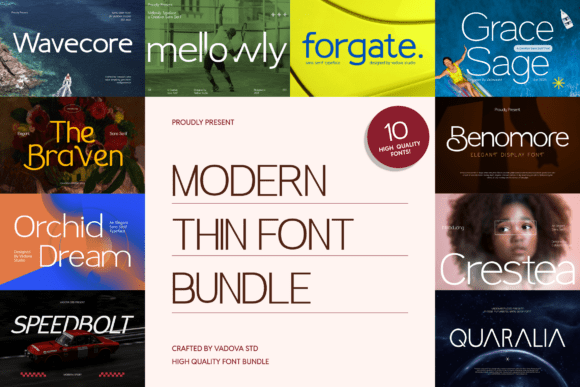
Modern Thin Bundle
Modern Thin Font Bundle – Revue détaillée
Le Modern Thin Font Bundle s’impose comme la référence incontournable pour tous les créatifs recherchant une typographie à la fois légère, élégante et ultra‑moderne. Cette collection regroupe des polices ultra‑minces qui allient clarité et raffinement, idéales pour les projets où la sobriété et le style sont primordiaux.
Points forts du bundle
- Design épuré : des proportions parfaitement équilibrées qui donnent une impression d’espace et de légèreté.
- Excellent rendu à l’écran : chaque fonte a été optimisée pour les interfaces digitales (sites web, applications mobiles, UI/UX).
- Lisibilité assurée : même en très petite taille, les caractères restent nets grâce à un tracé précis.
- Versatilité : convient aux identités de marque, aux mises en page éditoriales, aux packagings haut de gamme, à la mode et aux projets de branding.
Pourquoi choisir Modern Thin Font Bundle pour vos projets?
Que vous créiez une identité visuelle minimaliste, un magazine de mode ou un site e‑commerce premium, ce bundle offre une base typographique solide qui rehausse immédiatement le caractère professionnel de votre travail. Les traits fins apportent une touche de luxe sans sacrifier la lisibilité, ce qui est essentiel pour les titres, les sous‑titres et les citations accrocheuses.
Utilisations idéales
- Branding et logotypes modernes
- Mises en page éditoriales (magazines, catalogues)
- Design d’emballages de produits haut de gamme
- Interfaces web et mobiles (UI/UX)
- Supports publicitaires et affichage extérieur
Conclusion
En résumé, le Modern Thin Font Bundle est une collection indispensable pour les designers qui souhaitent allier minimalisme et sophistication. Ses polices fines offrent une esthétique premium tout en restant parfaitement lisibles, ce qui en fait le choix idéal pour tout projet recherchant une allure contemporaine et raffinée.